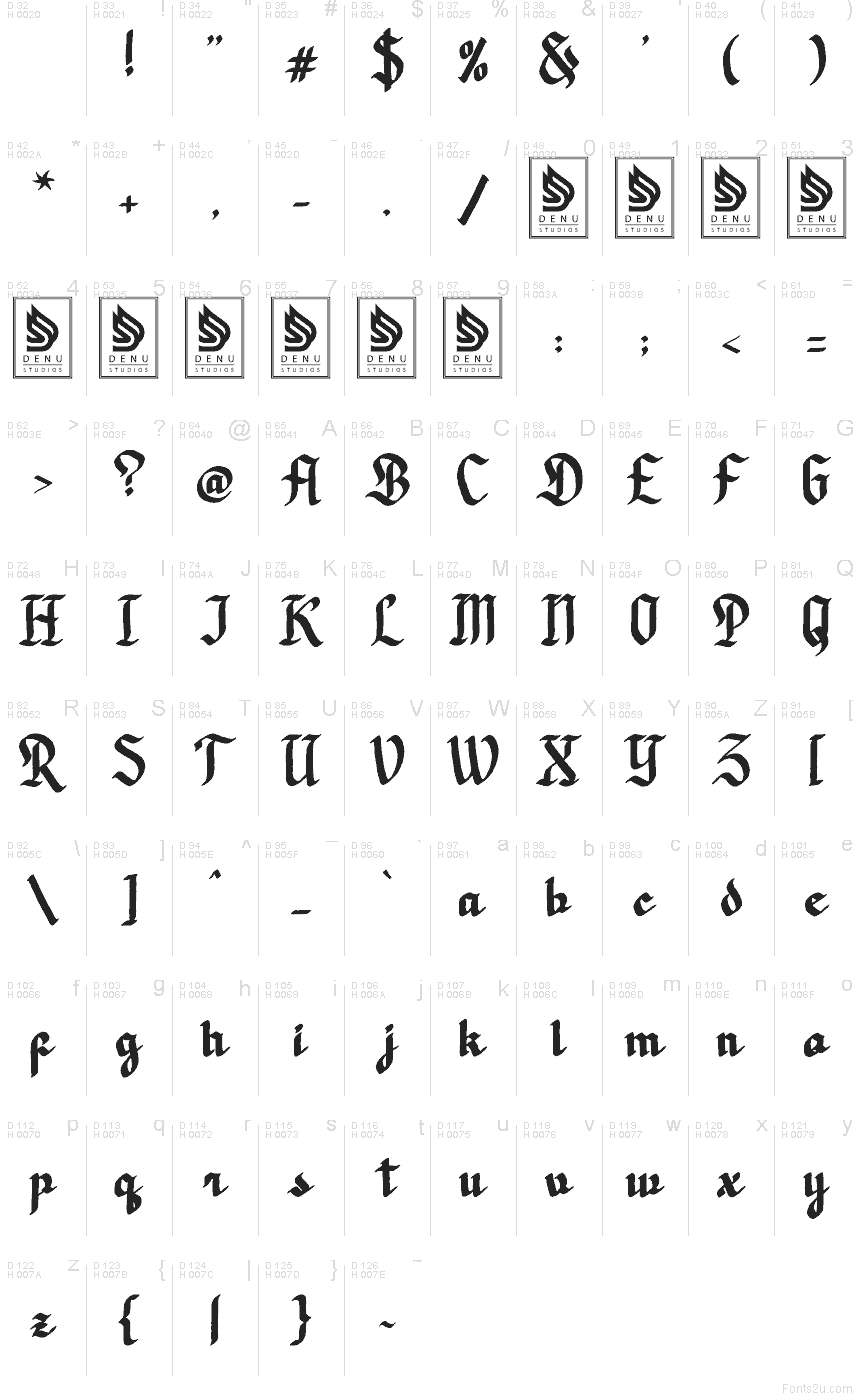
Dicaten od Denustudios je bezplatné, moderní gotické písmo s ostrým duchem blackletteru a překvapivě plynulým rytmem. Písmena kombinují vyřezávané, špičaté tahy s měkkými, oblými křivkami, takže textura působí na první pohled historicky, ale při čtení je čistší a aktuálnější.
Přirozeně zapadne do hudebního brandingu, na titulky plakátů, grafiku oblečení, obaly i obálky knih či zinů, kde trocha dramatičnosti pomáhá nést sdělení. Jako bezplatné písmo se Dicaten hodí také pro krátké nadpisy, skici loga, monogramy a titulní kartičky, protože zahnuté spoje a úhlové řezy dodávají i několika písmenům silnou siluetu.